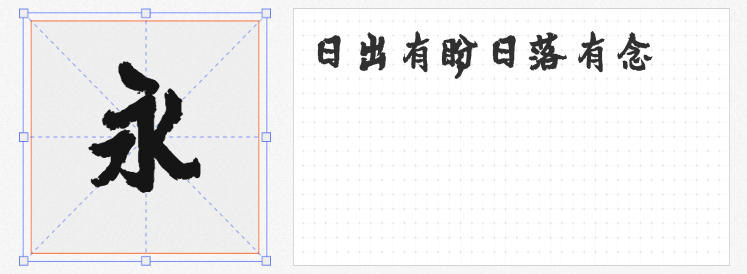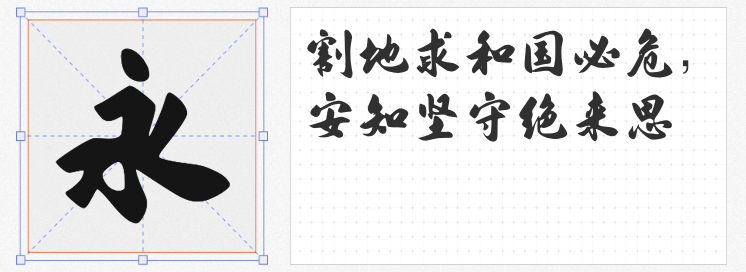
在商业海报的视觉竞争中,字体不仅是信息载体,更是传递情绪的“设计语言”。然而,版权风险与风格同质化常让设计师陷入两难。以下四款免费商用字体,以传统与现代交融的创意、开放授权的友好姿态,为海报标题注入鲜活生命力,助力实现零成本的高水准表达。
1. 字库星球飞扬体
由字库星球与甜奈网络联合研发的字库星球飞扬体,以传统书法为骨,现代设计为魂。其笔画如行云流水,起承转合间暗藏书写者的情绪张力,既保留了毛笔字的洒脱气韵,又通过结构优化适配屏幕显示。无论是国潮品牌宣传、音乐节海报的标题,还是需要传递“自由不羁”态度的创意设计,飞扬体都能以飒爽流畅的视觉气场点燃观众热情。
2. 云峰游戏标题简体
专为游戏、影视行业打造的云峰游戏标题简体,以粗犷有力的手写风格重塑标题的“战斗感”。刻意保留的飞白与笔画抖动,模拟出真实书写时的速度与力量,尤其适合动作类、竞技类海报的视觉轰炸。其高辨识度与强冲击力,亦能驾驭运动品牌、潮玩展等年轻化场景,用“不完美笔触”传递真实与热血。
3. 昆明海鸥体
作为全国首款融入红嘴鸥形态的创意字体,昆明海鸥体以灵动的笔画曲线模拟鸟类振翅的动态,兼具碑帖古韵与现代简约审美。叶根友团队通过海量模拟优化,使字体在隽秀中透出稳重气质,适用于文旅宣传、生态主题海报等场景。其“一字一景”的特性——笔画如鸥翼舒展,让标题本身成为一幅微型自然画卷。
4. 字体家AI造字霸行
由AI神笔与叶根友字体联合打造的字体,以几何化结构与锐利笔锋突破传统黑体框架。倾斜的笔画走向与切割式转折设计,赋予字体“破界而出”的未来感,适合科技产品发布会、电竞赛事等前沿领域的海报标题。作为AI生成字体的代表作,其免费商用模式更让中小团队得以低成本实现“大厂级”设计质感。
从书法逸趣到AI未来,从自然灵韵到手写热血,这四款免费商用字体以差异化风格覆盖多元需求。它们不仅为设计师提供安全便捷的用字选择,更以开放姿态推动创意民主化——让每一个好想法,都能找到最契合的视觉表达。